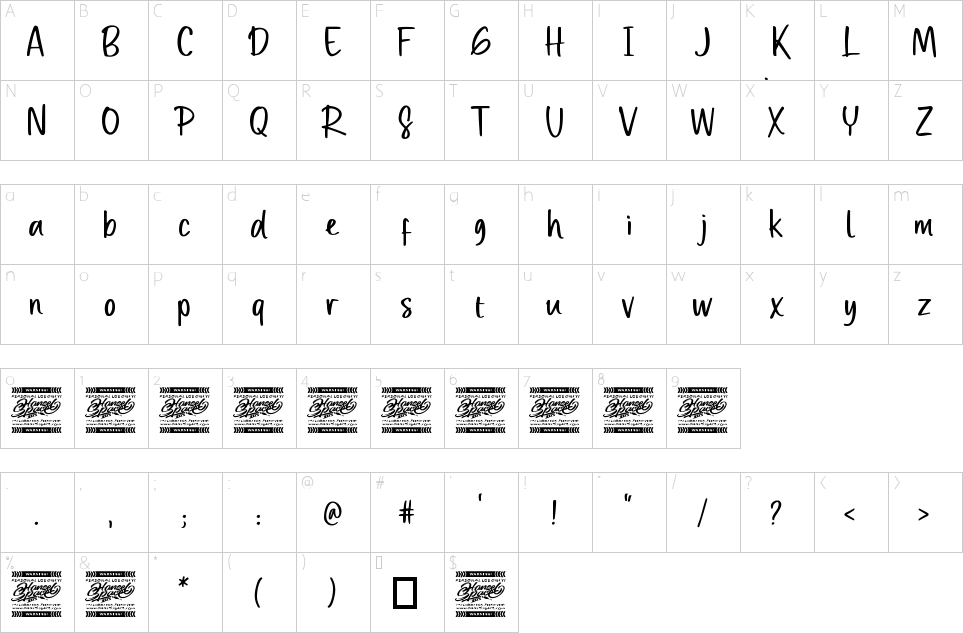
A fonte Porte Bon Heur oferece uma atmosfera envolvente e natural, perfeita para designers que buscam um estilo harmonioso e confortável em seus projetos. Desenvolvida por Hanzel Space, esta fonte é uma escolha ideal para aqueles que buscam uma solução versátil para textos tanto em desktop Windows quanto Mac. Suas linhas leves e a serenidade de seus traços evocam tranquilidade e calma, tornando-a perfeita para aplicativos como design gráfico, layout web e publicidade. Com a facilidade de download disponível gratuitamente, o Porte Bon Heur Font é uma opção ideal para estilos que valorizam a simplicidade e a elegância, proporcionando uma fonte de alta qualidade para seus projetos.